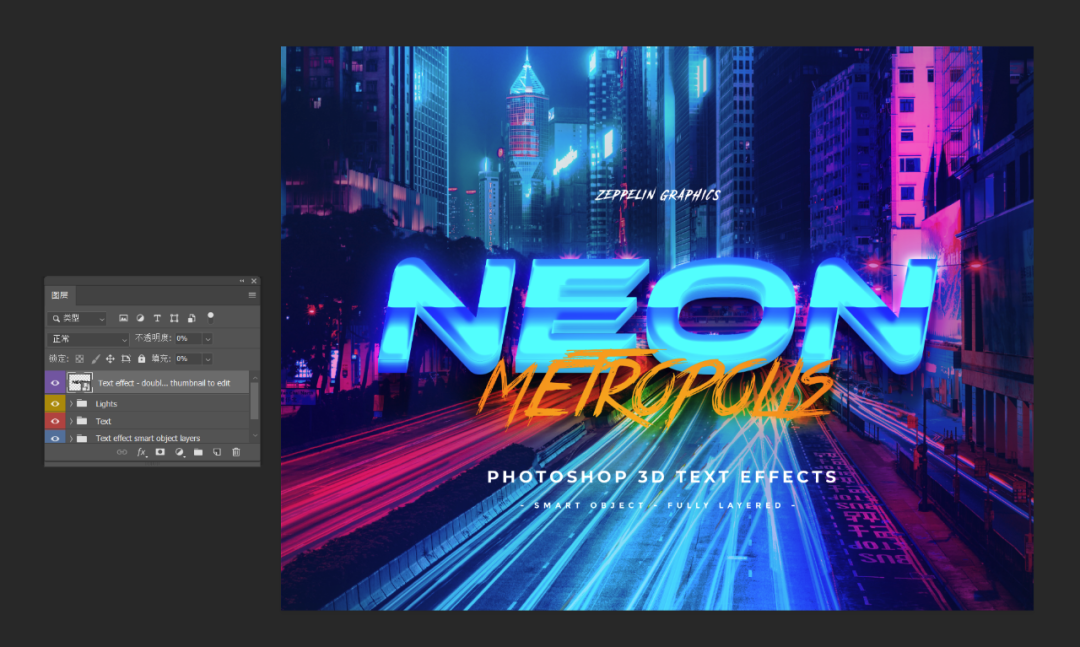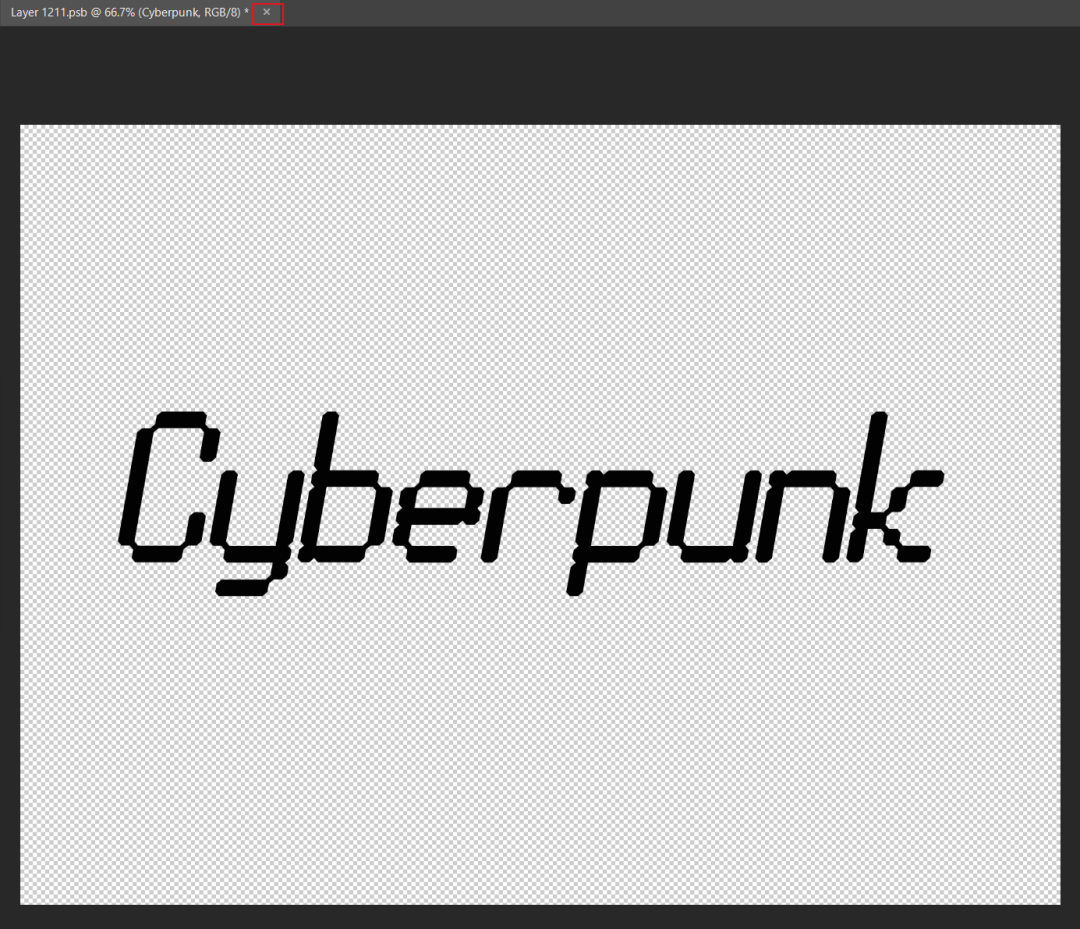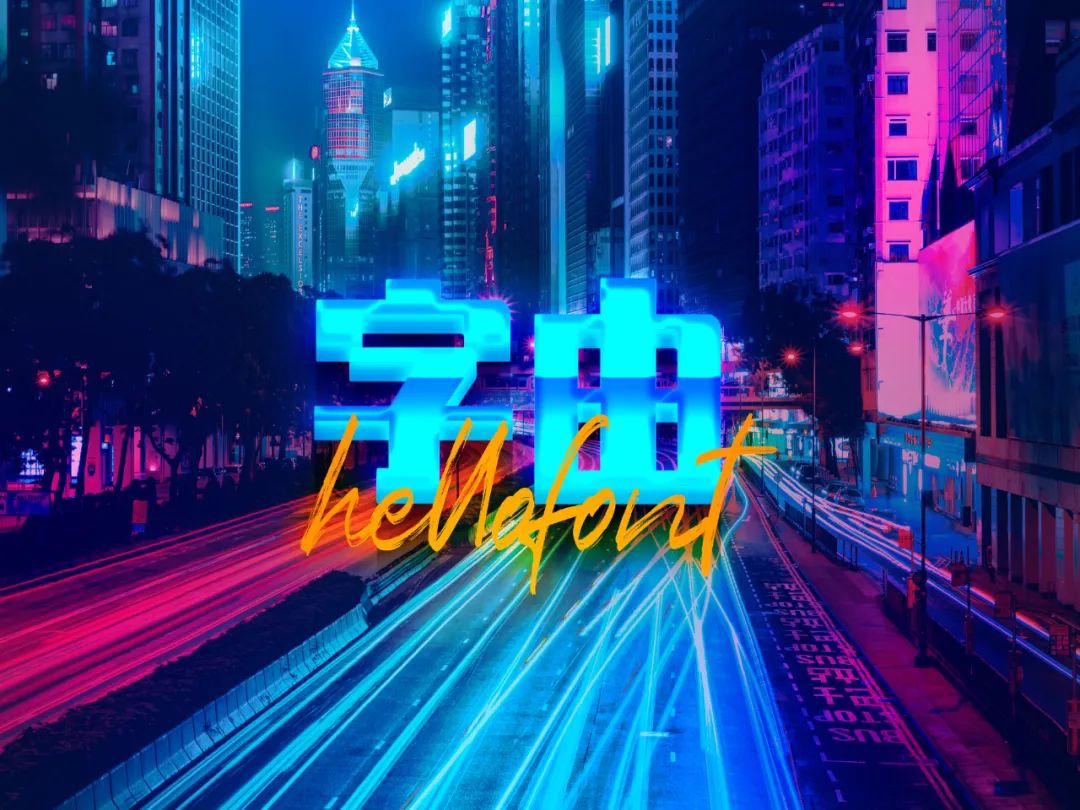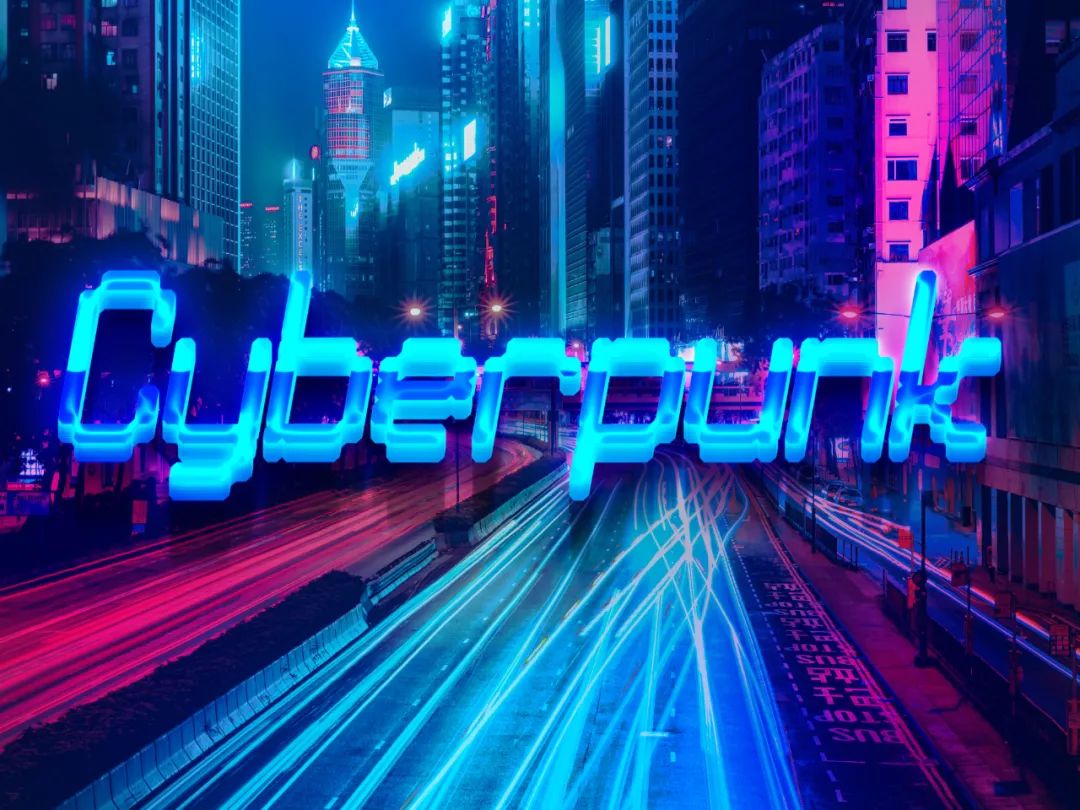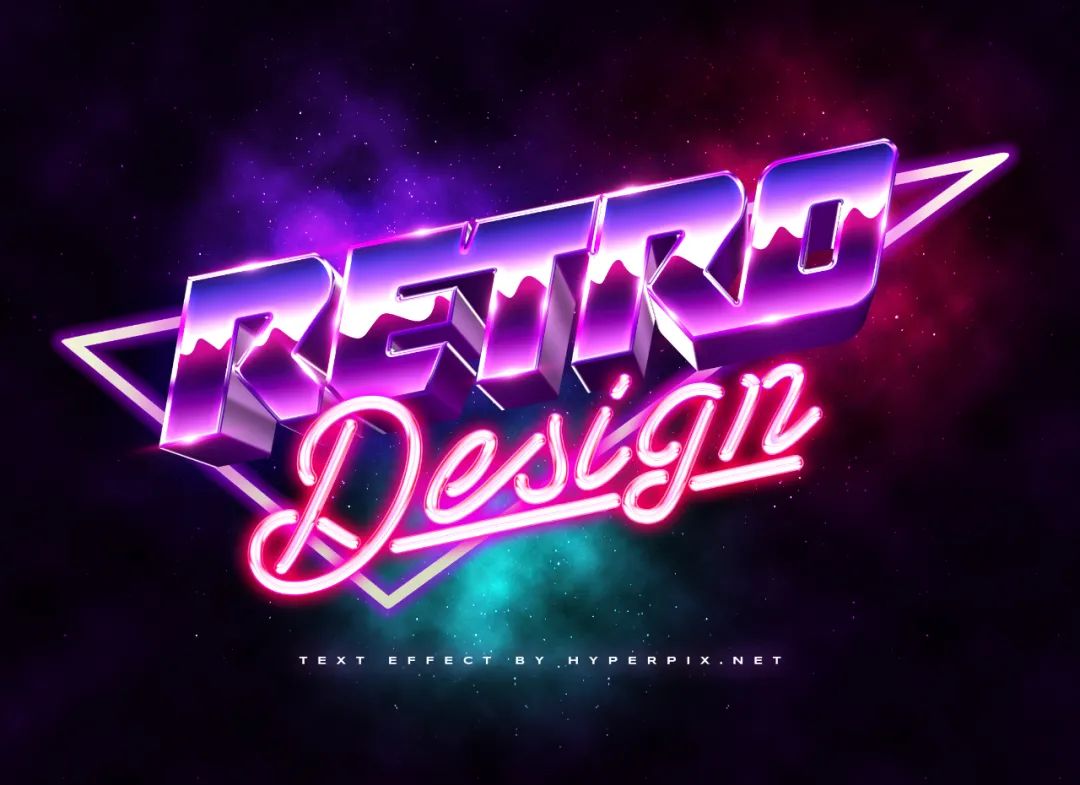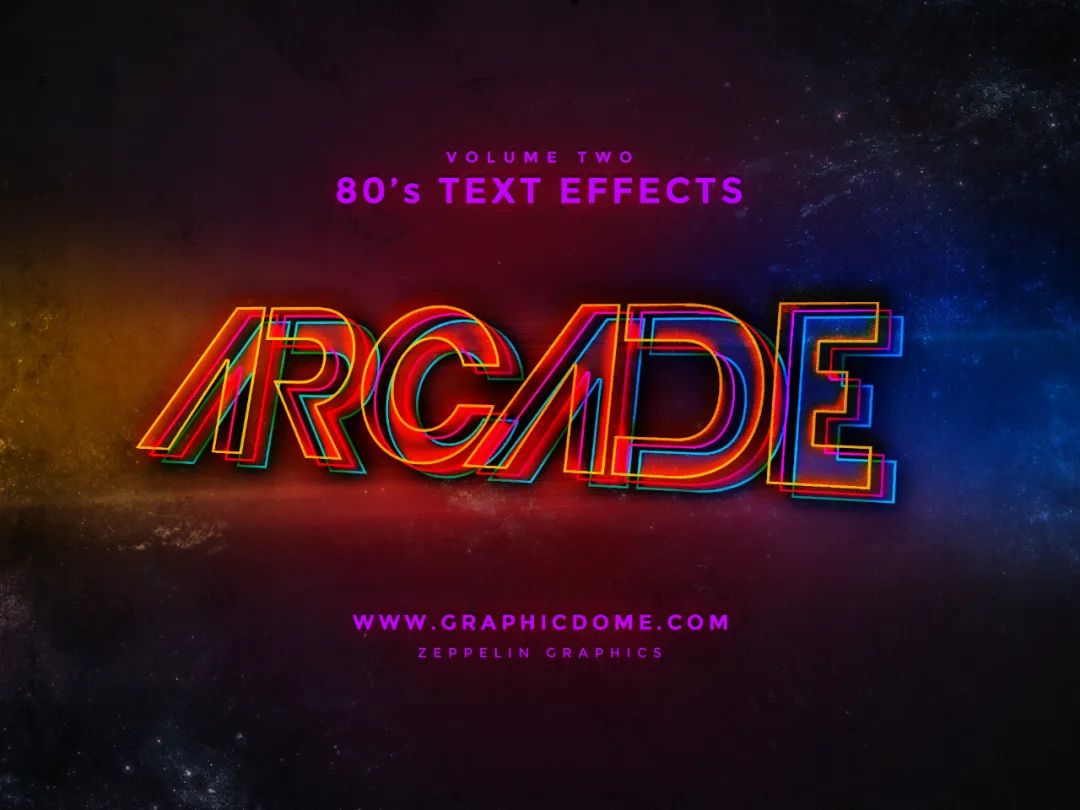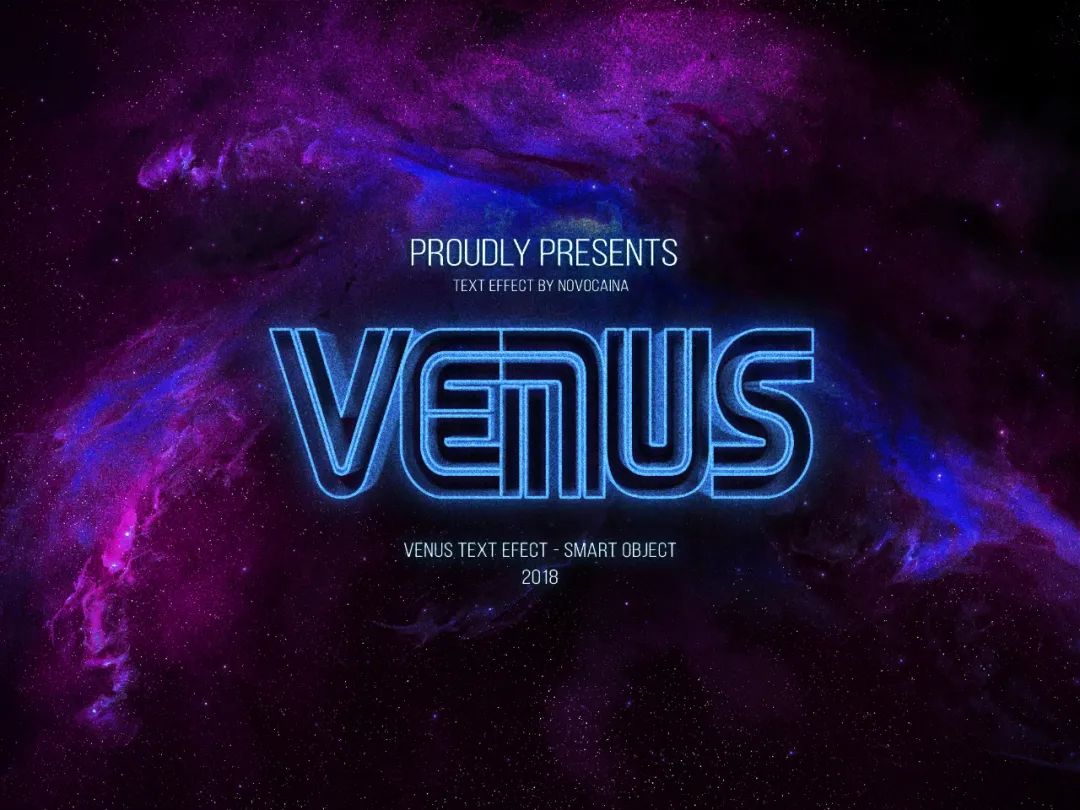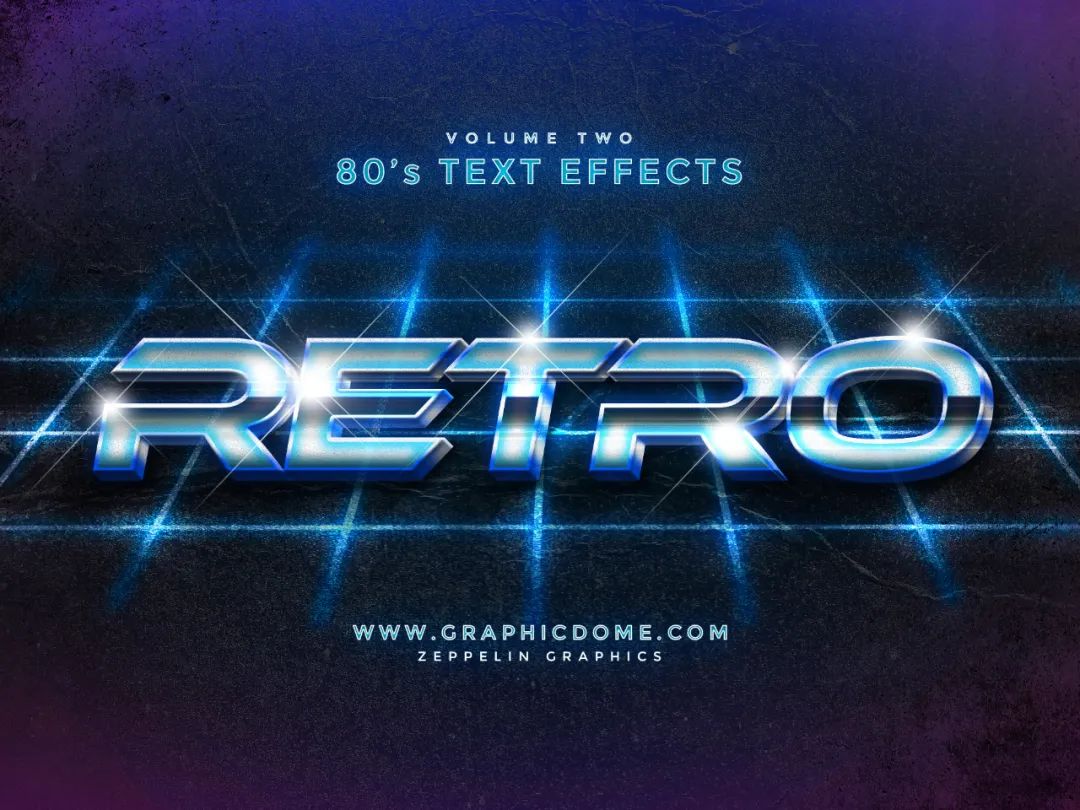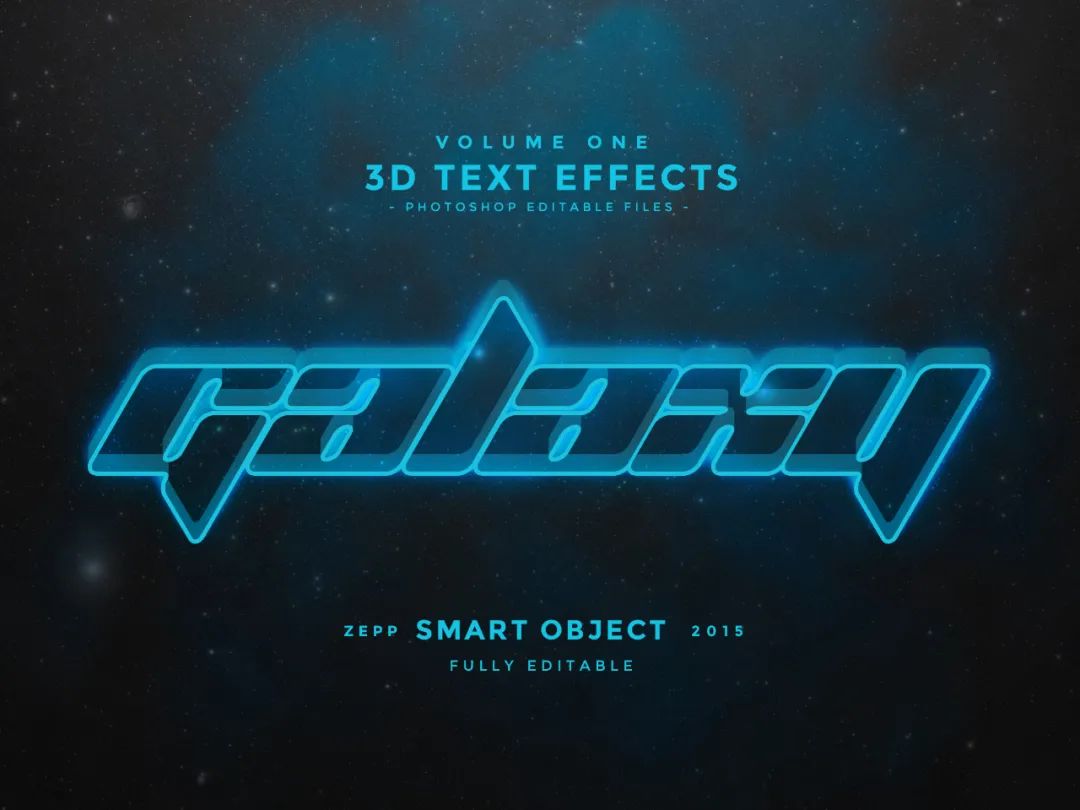
被《街舞3》的赛博朋克燃炸了?这就送你10个字体特效
不得不说,从第一季到第三季,《这就是街舞》把赛博朋克玩得越来越高级了。
不过这种大神才能hold的场景,对小白来说还是会有点压力,不妨先从字体开始,一点点营造那种霓虹感和未来感,今天就送你10个PSD源文件,一键轻松换字效~
然后你就进入了换字的页面,由于本身是不带字体的,所以会有小叹号,不过不用慌,上字由就可以了。我挑了个新上的免费英文字体——LL Black Matrix
然后收藏它,也可以直接在客户端搜索,记得激活小绿灯。接下来就是打上你的文案,选中字体图层,再点击客户端中的字体,立刻变。
为了突出未来感,我调整了一下字体(编辑——变换——斜切),再关掉此页面(点击上方的小X)。
当然你也可以选择中文字体,虽然没英文表现出众,但也有内味~这里用的是锐字真言体、Righteous(免费的就是香)。其它9个源文件,也都是类似的操作,你可以去一一尝试。